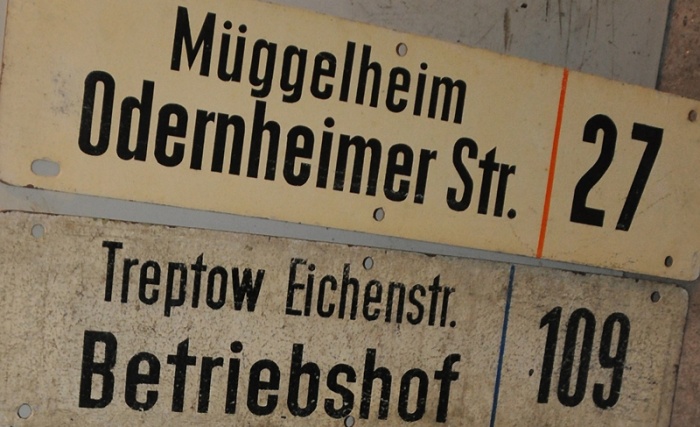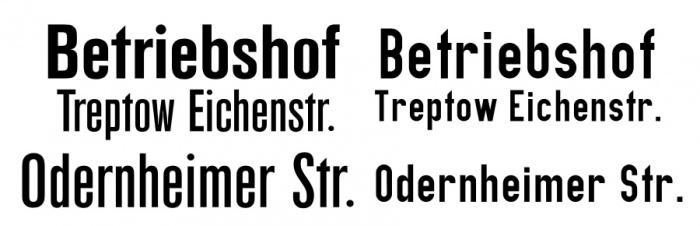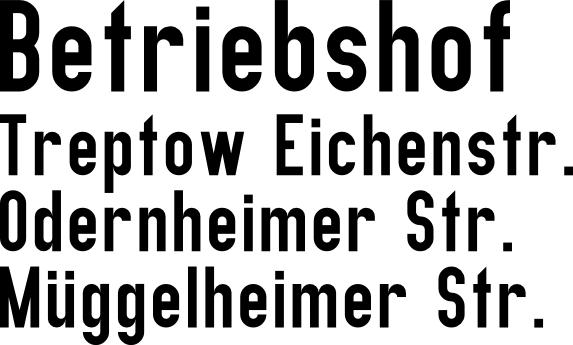
Eine weitere DDR-Schrift
Kann mir hierzu vielleicht jemand einen Tip geben?
Hat ein bischen Ähnlichkeit mit der "Plakativen Grotesk" und der "Berthold Akzidenz Gothic" finde ich.
Aber nicht genau. Bei den kleinen Buchstaben b, t usw. gibt es Unterschiede. Und beim großen S auch z.B.
Sieht alles aus nach einer mehr oder weniger gelungen ausgeführte Variante der Schrift der Königliche Preussische Eisenbahn von 1905. Diese wurde 1931 mit geringfügigen Änderungen als DIN Engschrift in der DIN 1451 aufgenommen. Beide Schriften stehen auf einem einfachen Raster (Hilfsnetz). Typisch für diese Schriften ist das b was links unten rund ist sowie das t was rechts unten keinen horizontalen Bogen hat und oben diagonal abgeschnitten wird. Die Musterzeichnung der Preussischen Eisenbahn und das DIN Normblatt waren in ihrer Ausführung recht grob. So hatten beispielsweise die Rundungen keinen Überhang zur Schriftlinie und x-Höhe. Bei Bedarf haben die Schildermaler also, je nach können, die Schriften etwas besser gemalt als vorgegeben. Oder auch noch einfacher. Schilder wie diese wurden damals noch nicht als Teil des Unternehmensauftritts gesehen. Es war alles ‘Zweckbeschriftung’ die bei Bedarf auch ‘von Ungeübte’ ausgeführt werden sollte.
Nun zu die hier gezeigte Varianten: Das gemeine o und n der KPE-Schrift und der DIN Engschrift sind genau 3 Einheiten breit und 5 Einheiten hoch. Bei der DIN Mittelschrift waren das 4 und 5. Aufbauend auf diesem System konnte man auch eine noch schmaler aussehende Schrift konstruieren. Beispielsweise so, dass die Breite ebenfalls 3 Einheiten, die x-Höhe aber 6 Einheiten hoch war. Das scheint hier der Fall gewesen zu sein. Obwohl es sehr viele Anwendungen solcher Schriften gegeben hat, hat es nie eine KPE-Musterzeichnung oder DIN-Normblatt gegeben, was eine Schrift mit derartige Proportionen enthalten hat. Hierfür hat man sich auf Kundenseite wohl auf die Fähigkeiten des Schildermalermeisters verlassen. Es kann aber eine sogenannte Werksnorm eines Eisenbahnwerkes oder Schilderherstellers gegeben haben. Im Idealfall wurden solche Werksnormen ergänzend zu den DIN Normen angelegt. Wahrscheinlich sind auch für die hier gezeigte Schriften solche Art von Vorlagen entstanden. Die CST Berlin-East ist eine Interpretation solcher Vorlagen und/oder Schilder. Der genauere Werdegang kann man in der Lektüre über dieser Schriften von Verena Gerlach und Ole Schäfer nachlesen.
N.B: Die Schriften der aktuellen DIN 1451 wurden zuletzt als DIN 1451-2 überarbeitet und dabei genauer definiert. Seitdem haben die Rundungen eine Überhang und gibt es die typische Buchstabenformen von b und t nicht mehr. In der DDR wurden die DIN Normen zuerst weitergeführt, danach in TGL umbenannt und teilweise überarbeitet. Die TGL Normblätter für Schrift haben so weit mir bekannt keine extraschmale Schrift enthalten.
Ich habe die Preußische Musterzeichnungsschrift auf dem Rechner und mal einen Vergleich erstellt.
Da ich mich nicht so gut auskenne mit dem Bearbeiten von Schriften, habe ich sehr lange gebastelt, um die Berthold Akzidenz Gothic annähern an die Schrift von den Schildern anzupassen. Das Ergebnis ist nicht perfekt, aber ich bin durchaus erstmal damit zufrieden. Den eckigen I-Punkt habe ich durch einen runden ausgetauscht. Das b habe ich entsprechend links unten abgerundet (durch Zuhilfenahme des kleinen "e"), das M habe ich verändert, das kleine p  usw. Als nächstes sind die Ziffern dran ...
Leider weiß ich nicht, wie man die Breite der Buchstaben und Ziffern einheitlich hinbekommt, ich denke aber, daß man etwaige Abweichungen kaum sieht. Besonders schwierig finde ich z.B. die Rundungen des "Bogens" in der 2 ... da habe ich gestern bestimmt 1 Stunde dran gesessen.
Links im Bild (untereinander) die von mir transformierte Berthold Akzidenz Gothik. Rechts (untereinander) die Preußische.
Nicht übel! Du hast ja Glück, in den 30ern wurden in der Entwurfsphase die DIN Schriften an die Akzidenz Grotesk angepasst (siehe Versal S in der DIN Mittelschrift) auch die Akzidenz Grotesk wurde an die DIN Schrift angepasst (zumindest für die Erstellung der Normblätter). Zumindest theoretisch ist es also nicht verkehrt mit der Akzidenz Grotesk anzufangen. Ich kenne aber keine Akzidenz Grotesk von Berthold die Akzidenz Gothic oder Gothik heißt oder hieß …
Fantastisch! danke für diese spannende Typestory, da kommt keiner Tatort (bis auf die Münsterische) mit. Als diplomierter verbürgter Din Schrift Hasser finde ich die Preuss. Fassung eigentlich ganz lustig. Was alle diese Schriften haben, wie Albert Jan bereits ausführlich dargestellt hat, sind formen die leicht nach zu machen sind. Daher sind fasst alle Rundungen wie beim s und e aus Cirkelteile und mit geraden zusammen gelegt. Die Akzidenz ist dagegen bereits freiformig elegant.
Danke, trotzdem brauche ich als Laie ewig für solche Anpassungen. Wenn ich wüßte, wie ich es machen muß, würde ich mir die Schrift 1:1 nachbauen.
Ich habe genug Vorlagen als Schilder. Aber soviel Geduld und Talent habe ich wohl nicht.
Ich kenne aber keine Akzidenz Grotesk von Berthold die Akzidenz Gothic oder Gothik heißt oder hieß …
Asche auf mein Haupt! Ich hatte mich verschrieben. Ich meinte natürlich "Grotesk" statt "Gothik" ...
Ich suche auch schon wieder eine "neue", da ich noch einige Abziehbilder nachgestalten muß.
Peter Wiegel, der ebenfalls in diesem Forum aktiv ist, hat seine Version der Schrift nach der Preussischen Musterzeichnung IV 44 zum Download bereitgestellt. Mit dieser kommst du der gesuchten Schrift auch recht nah – wenigstens näher, als mit der Akzidenz Grotesk.
In ganz groben Zügen ist das Original wohl eine individuelle Wiedergabe der alten Schriftmuster der Engschrift nach DIN 1451 vom 1906 oder kurz später.
Danke, ich finde diese Schrift zu stark abweichend und werde einfach meine selbst zusammengebastelte obige Variante nutzen.
Inzwischen fand ich übrigens noch die Filmotype Ginger und Glenlake, die beide auch nahe an Originale Vorlagen aus der DDR heranreichen.
Beide waren mir bisher völlig unbekannt, ich bin sehr froh, sie nun entdeckt zu haben.